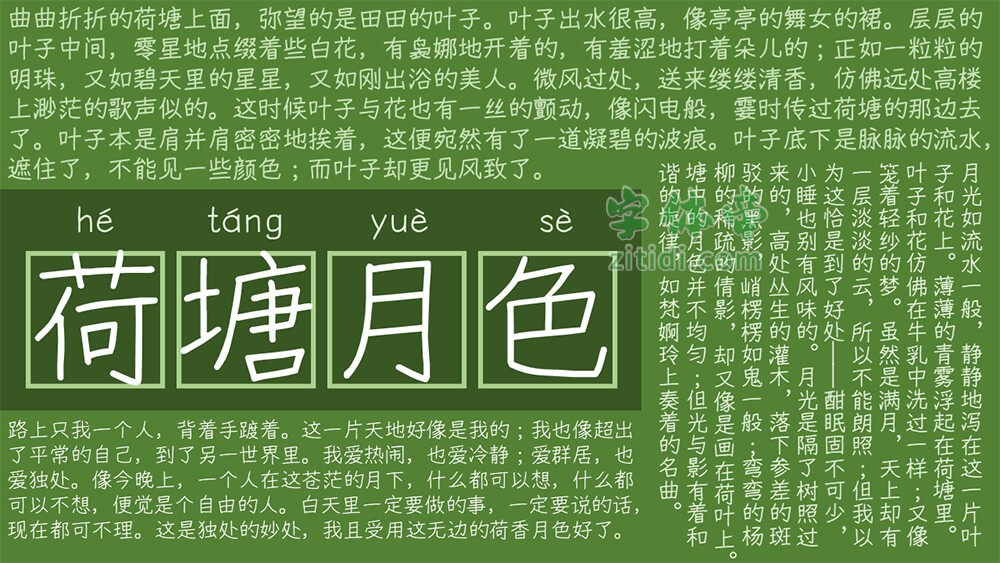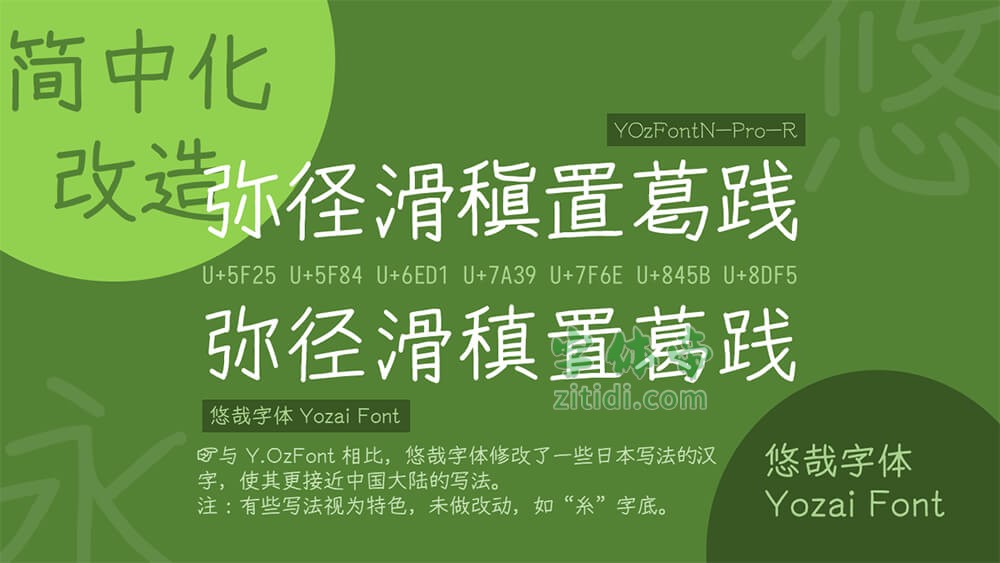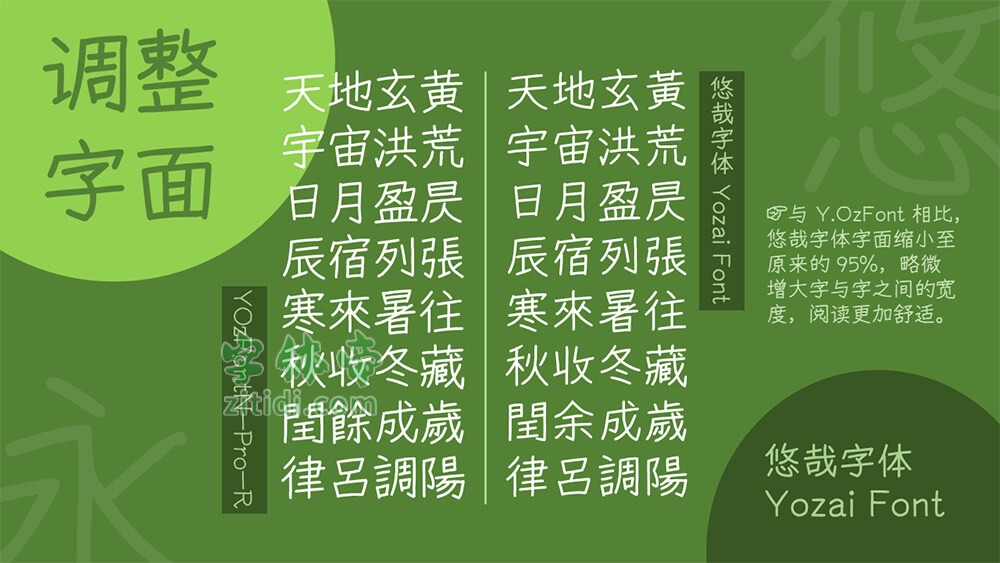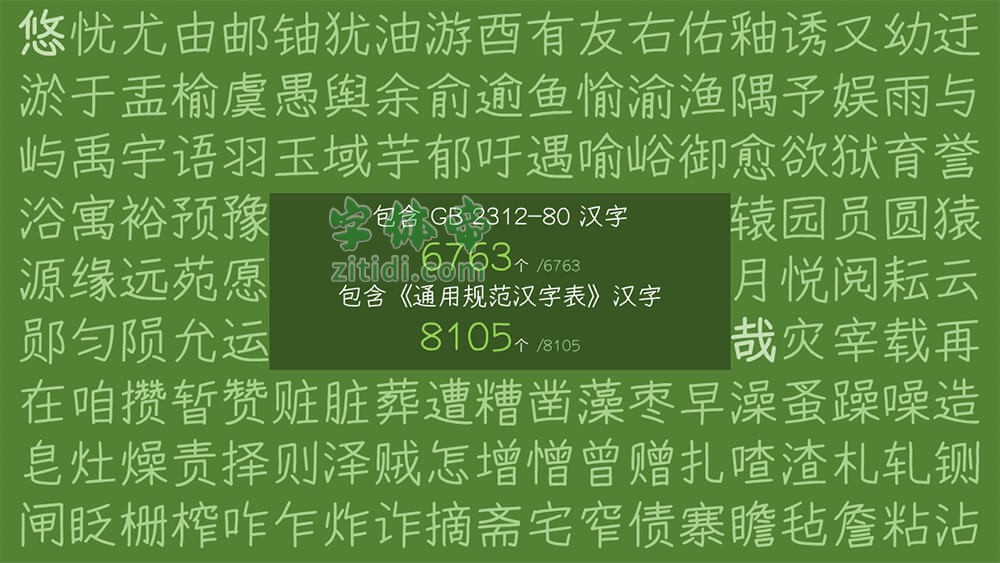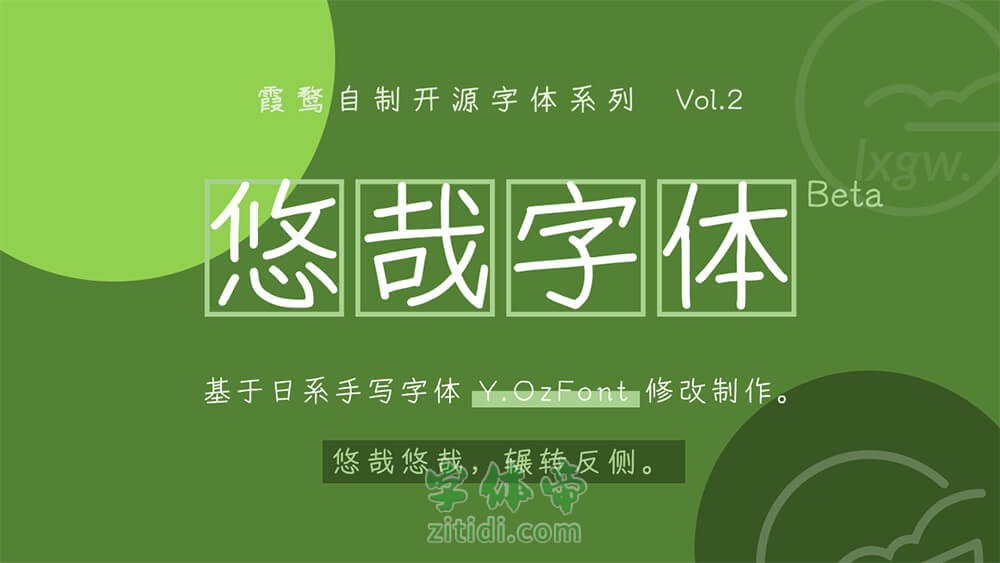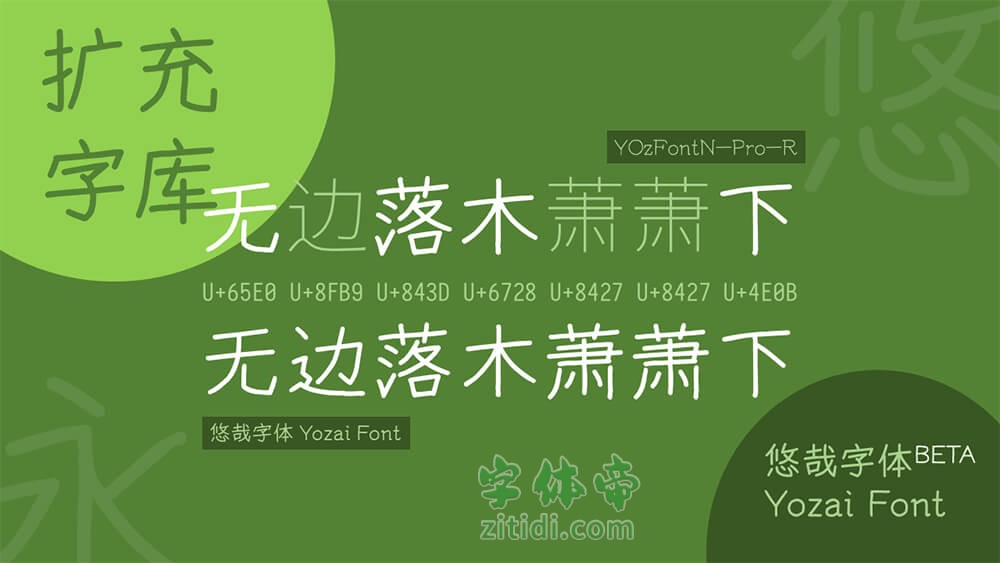
悠哉字体是一款基于Y.OzFont的手写风格的字体。利用原字体中已有的笔划和部件,通过拼接和调整造出新字 (必要时自己用鼠标写出部件) 。目前已补全原字体中有对应繁体字的简体字,以及GB 2312范围内的所有汉字,并根据jf Open 粉圆的字库补全了繁体中文的常用汉字 (包含台湾教育部门规定的 4808 个常用汉字) 。
悠哉字体在原Y.OzFont的基础上,字面缩小至原来的95%,优化西文和标点符号的显示;修改部分汉字的写法,使其接近中国内地的规范字形。由于原版字形偏细,从0.715版本起,新增Medium (中等) 字重。
注意事项
- 本字体仍处于测试版,部分汉字还是处于日本写法,且字库并不是很全。 计划 补全 GB 2312 范围内的所有汉字,并更正 GB 2312 内汉字的写法为中国内地的字形。
- 本人并不是专业的设计师,并未考虑设计美感,所以看起来可能略丑,补进去的字与原版可能略有违和感,但是聊胜于无。